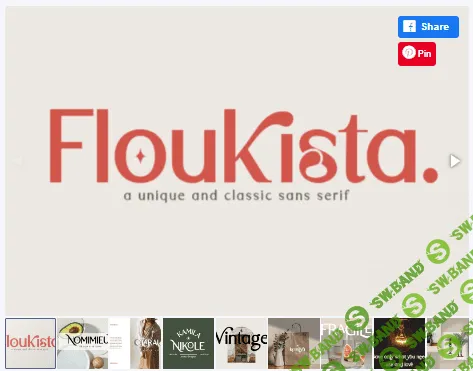
Автор: creativefabrica
Название: Floukista Font (2022)
Floukista — это минималистичный, современный и элегантный шрифт без засечек с красивыми лигатурами, множеством специальных альтернативных глифов, орнаментов и многоязычной поддержкой. Это универсальный шрифт, который отлично работает как в больших, так и в маленьких размерах. Floukista идеально подходит для брендинга проектов, дизайна логотипов, брендинга одежды, упаковки продуктов, заголовков журналов или просто в качестве стильного наложения текста на любое фоновое изображение.